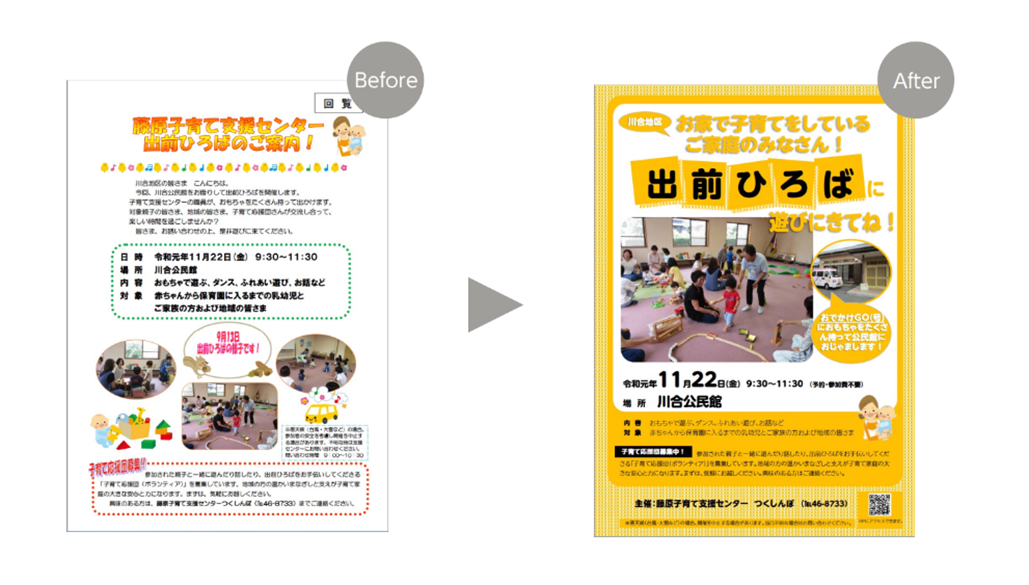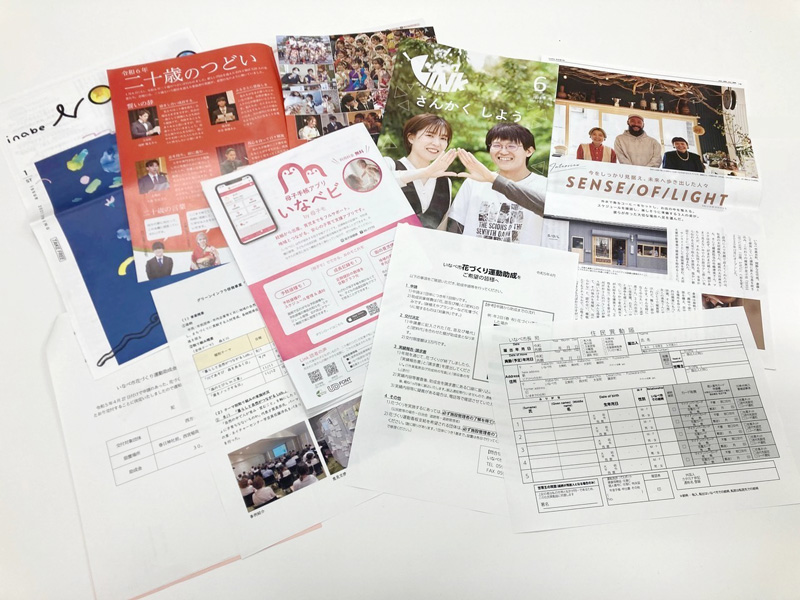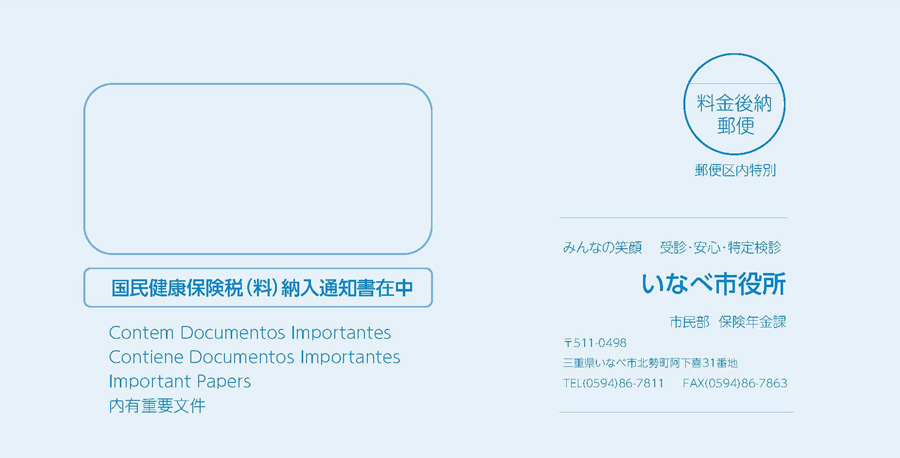
UDフォントで変わった
自治体情報発信マインド
「SDGs未来都市」に選定されている三重県いなべ市は梅林公園の再生や、脱炭素に向けた事業など、先進的な取り組みをさまざまにおこなっている。市の内外にその魅力を発信する機会が多いなか、情報がより多くの方に「伝わる」ために導入したのがUDフォントだ。故郷に「誇りと愛着」を持てるようブランド力を強化している日沖靖市長に、UDフォントの活用法や今後の展望などについて伺った。
UDフォントを使っていかに「伝わる」情報へ仕上げるか
私がUDフォントと初めて出会った時、その圧倒的な読みやすさに驚きました。当市は「いなべ市広報戦略基本方針」を掲げ、職員全員が広報マインドを持って情報発信を心がけていますが、UDフォントはそんな私たちになくてはならないものだなと。そこで2019年度に、全ての職員PCにUDフォントを導入しました。
現在は、市からの広報紙やWebサイトはもちろんですが、通知文チラシ、申請書など職員が作成するコンテンツに日々、活用しています。
施政方針を作成する時も私はUDフォントを使用しています。見る人が読みやすいようにと以前はゴシック体を太字にしていましたがUDフォントはその必要がなく、しかも文書を作っている私自身、非常に読みやすいです。
ただ、UDフォントを使えば万事OKというわけではありません。このことを教えてくださったのはモリサワさんです。モリサワさんはフォントを開発・提供するだけでなく、広報物がより「伝わる」にはどうすればよいかを常に考えておられ、当市の職員に向けても研修をおこなっていただきました。
研修では、実際に各課で使用中の書類をブラッシュアップしたのですが、必要な情報とそうでない情報の整理の仕方や、見やすいレイアウト手法、効果的な余白の取り方などについて教えていただきました。おかげでいなべ市職員の資料作成スキルが上がることにより、広報マインド、市民サービスの向上につながっていると自負しています。
スキルアップだけではない!
研修で生まれている好循環
UDフォントは内部向け資料にも外部向け資料にも幅広く使用しています。例えば外部向け広報物の1つに、国民健康保険の封筒があります。「何の封筒」であるかが一目でわかるよう「国民健康保険」の文字ウエイトを意識して強調するなど、フォントの力に頼るだけでなく情報にメリハリを付け、市民に開封してもらえるように配慮しています。
一方、内部向け資料として、議会へ提出する文書があります。この資料を読むのは議員さんなのでUDフォントを使うのはもちろん、議員さんたちが読みやすいよう職員は研修で学んだことをもとに自発的に配慮をするようになりました。
こうした変化はモリサワさんの研修の賜物だと感じています。私はあらゆる面で職員の自主性を重んじていますので、UDフォントの使用や研修への参加は任意としていますが、受講した職員らはUDフォントの有用性を大いに実感。今まで延べ67人が研修を受講するなか、まだ受講していない職員に資料作成のコツを教える動きが出てくるなど、UDフォントを軸とした好循環がいろいろと庁内で生まれています。
UDフォントを使った授業で「伝わる」大切さを実感した中学生
市内の小中学校に導入したタブレット端末にも、UDフォントを採用しています。より、「伝わる」資料について小中学生にも学んでもらえたらと、モリサワさんにはいなべ市立 藤原中学校でも授業をおこなっていただきました。
授業では、SDGsに関する情報発信の取り組みとして『いなべティーンフェアトレードブック』を制作。生徒たちはUDフォントの使い方や資料のレイアウト方法などを学んだのち、フェアトレード商品を扱う市内30箇所以上の事業所を取材し、その特徴などをレポートにまとめました。
今まで資料を作ったことがなかった生徒も、フォントを変えたり写真の大きさを揃えたりすることで読みやすさがかなり変わることを体験。さらに自分たちが学んだことを小学5年生に教える授業を通し、資料作りのコツを浸透させていきました。
「伝わる」を考えることは人の成長過程でとても重要です。相手がいるから、相談もできるわけですね。このようなことを理解するうえで、学びの場で「伝わる」とはどういうことかを考え、理解し、自分で作るスキルを経験できる機会を作れたことはとても有意義だと思います。ぜひ、モリサワさんと今後も協力し合い、子どもから大人まで、より伝わる関係を市としてもバックアップしていきたいと思っています。
いろいろな気づきを与えてくれるUDフォントが今後、社会のスタンダードになったらいいなと思います。またモリサワさんがおこなわれている啓発活動も継続して、市内の学校での授業や職員向けの研修をぜひ今後ともお願いできたらと考えています。